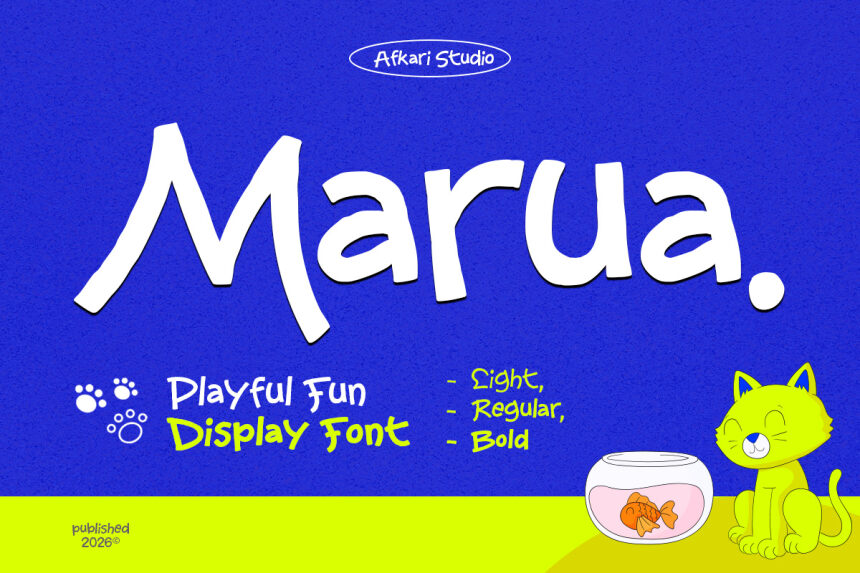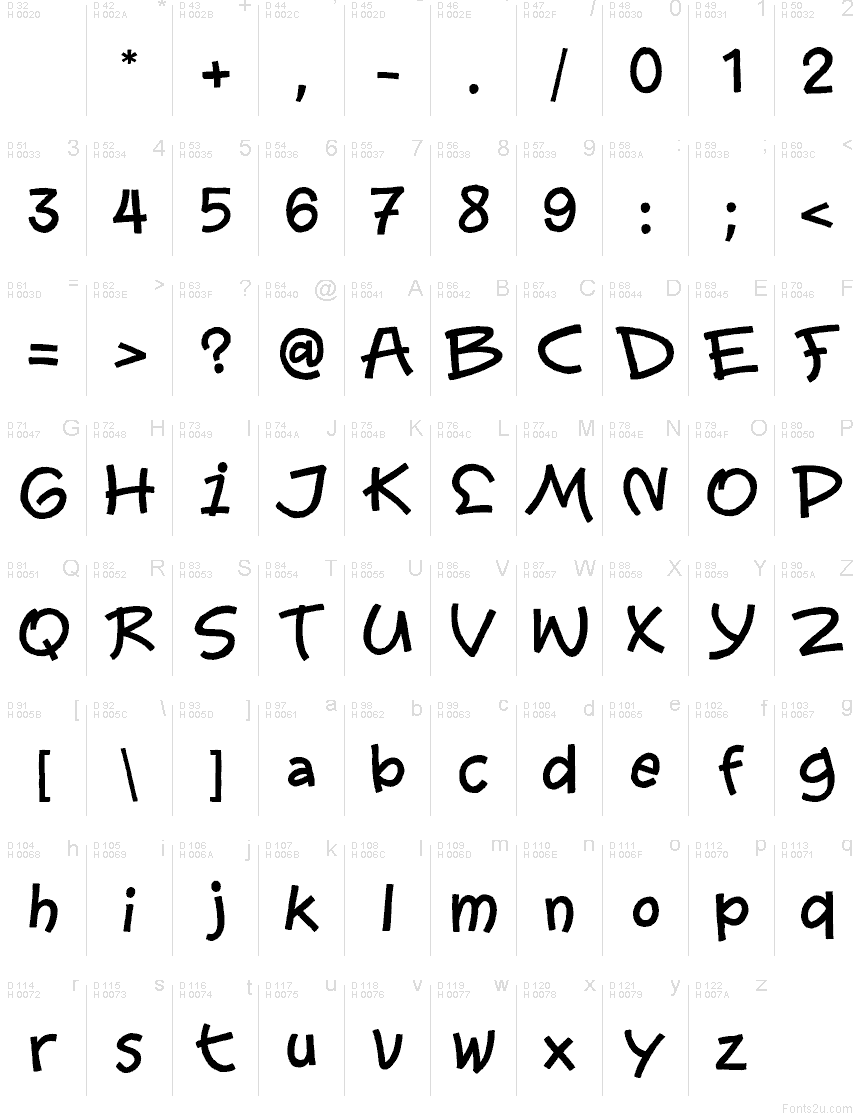
Marua, de Afkari Studio, es una tipografía display gratuita estilo cómic con un aire desenfadado y hecho a mano. Sus letras transmiten un carácter lúdico sin llegar a ser infantiles, con curvas irregulares, trazos robustos y un ritmo ligeramente irregular que le aporta al texto una voz humana y casual.
Es perfecta para titulares de pósteres, portadas de libros infantiles, letreros de cafeterías, pegatinas y tarjetas para redes sociales, donde un tono amable y poco convencional ayuda a transmitir el mensaje. Como fuente gratuita, Marua funciona mejor en frases cortas y nombres, ya que esas curvas vivaces y proporciones tambaleantes le dan suficiente presencia incluso a unas pocas letras para sostener todo un diseño.